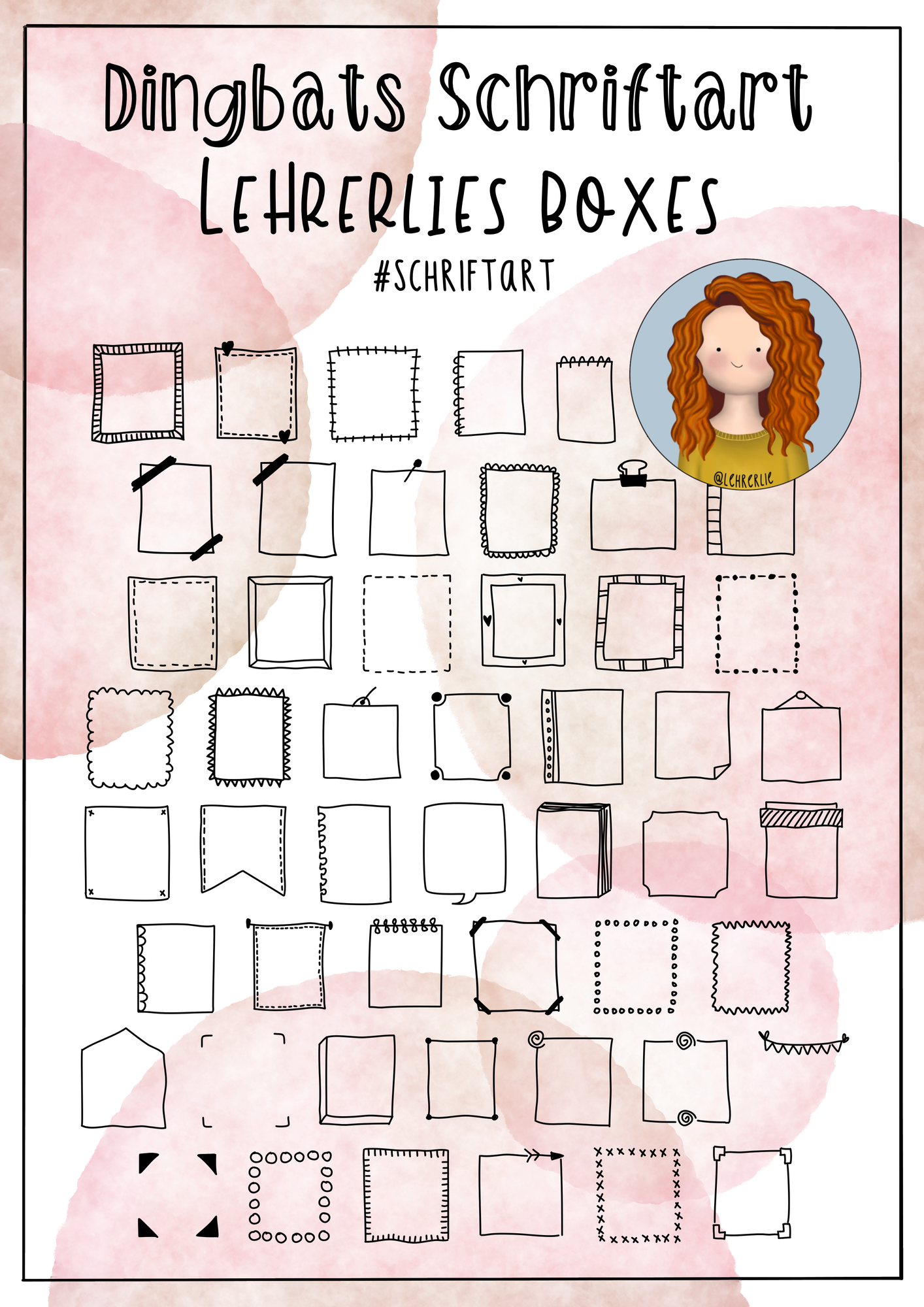
In diesem Material erhaltet ihr eine Dingbats-Schriftart. Sie besteht aus über 50 Rahmen und Kästchen im Sketchnote-Style, mit welchen ihr eure Materialien in allen gängigen Programmen super einfach gestalten könnt. Einfach die Schriftart installieren und mit dem beiliegenden Fontposter das gewünschte Element auswählen.
Dingbats-Schriftart: Lehrerlies Boxes // Sketchnotes